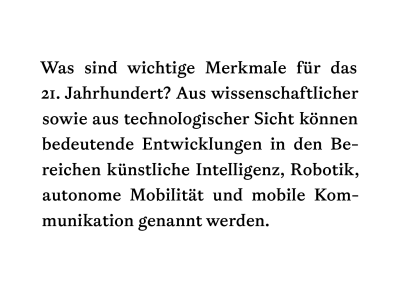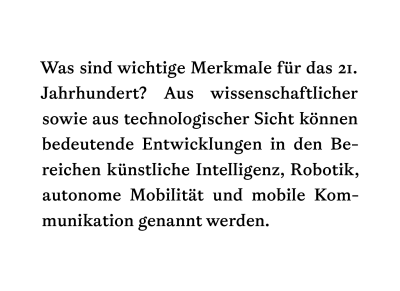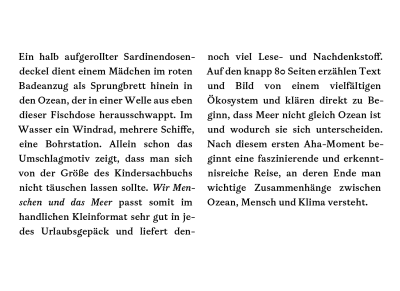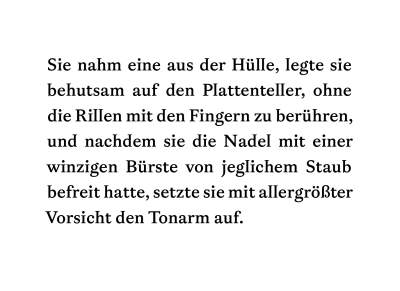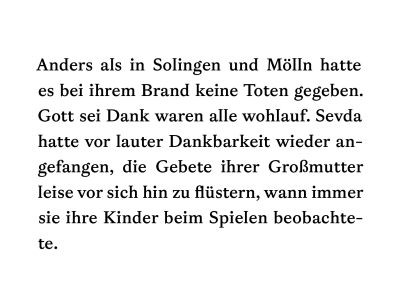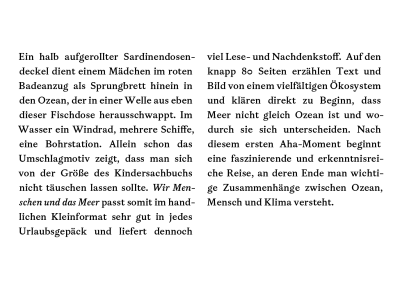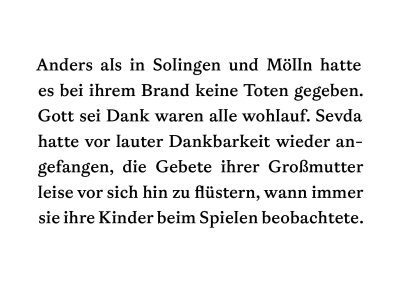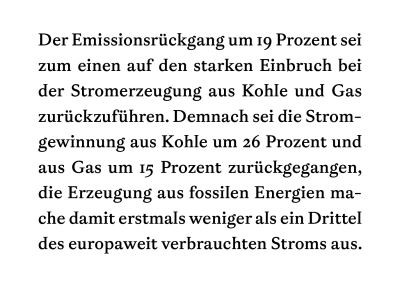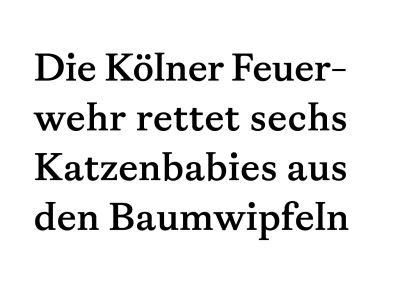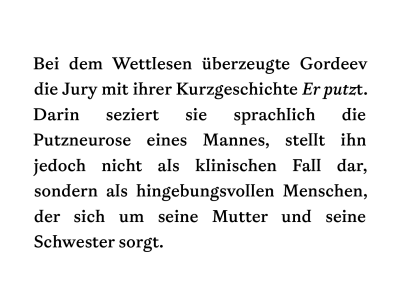
Blocksatz kennt man meist aus Büchern, Zeitschriften oder Zeitungen. Es handelt sich um eine Satzart, bei welcher der Text »blockig« gesetzt wird: Alle Zeilen werden auf die gleiche Länge gebracht.
Ist der Blocksatz sorgfältig nachbearbeitet, ergibt sich ein ruhiges Textbild. Durch seine geraden Satzkanten wirkt der Blocksatz statischer als offenere Satzarten wie der Flattersatz.
Bevor man mit der typografischen Arbeit beginnt, ist es wichtig, die richtige Textsprache einzustellen. Sonst kommt es bei Zeilenumbrüchen zu fehlerhaften Trennungen.
Manchmal wirken die Satzkanten trotz des Blocksatzes optisch nicht gerade. Hier kann der optische Randausgleich helfen. Dabei werden kleine Zeichen wie Trennstriche automatisch über den Textrahmen rausgezogen. Da dies die Umbrüche ändern kann, ist es ratsam, diese Einstellung schon zu Beginn zu aktivieren.
In InDesign:
Den optischen Randausgleich findet man unter Type > Story.
Schnell entstehen im Blocksatz unschöne Löcher und Ameisenstraßen. Besser wird es, wenn Trennungen in bestimmten Maßen zugelassen werden.
Durch vorsichtiges Justieren von Wort- und Buchstabenabständen erhält man ein ruhigeres Satzbild. Beides lässt sich in Textsatz-Programmen definieren. Das braucht etwas Geduld und Übung, aber es lohnt sich für das sehende und lesende Auge.
In InDesign:
Trennungen können in den Paragraph Style Options > Hyphenation definiert werden.
Feintuning kann man beim Blocksatz über die Paragraph Style Options > Justification > Wordspacing, Letterspacing vornehmen. Hierbei unbedingt den World-Ready Single Line Composer nutzen.
Zwar sind wir beim Blocksatz unflexibler, achten aber trotzdem auf das Zusammenbleiben von Sinneinheiten. Was hilft: mit Nonbreaking Spaces arbeiten. Diese schützenden Leerzeichen bewahren vor ungewollten Umbrüchen.
In InDesign:
Die Nonbreaking Spaces findet man unter Type > Insert White Space > Nonbreaking Spaces.
Unser Auge leistet viel beim Lesen. Auch wenn wir als geübte Lesende getrennte Worte leicht wieder zusammenziehen, sind Worttrennungen am Ende der Spalte eine Leseherausforderung, die man vermeiden kann.
Einen Absatz mit einem getrennten Wort abzuschließen, ist nicht nur sprachlich, sondern auch visuell unelegant. Um dies zu umgehen, muss man manchmal schon einige Zeilen zuvor den Text anders umbrechen lassen.